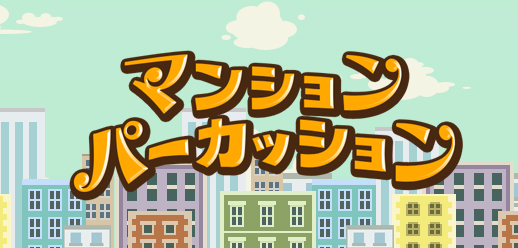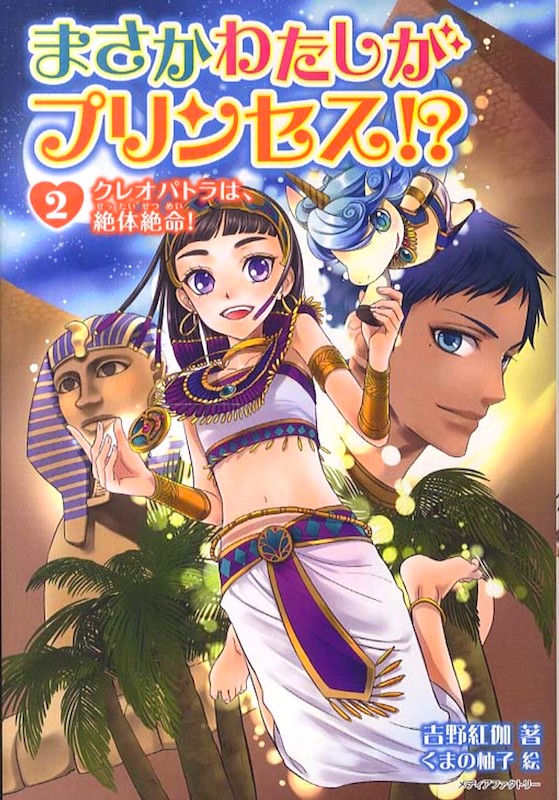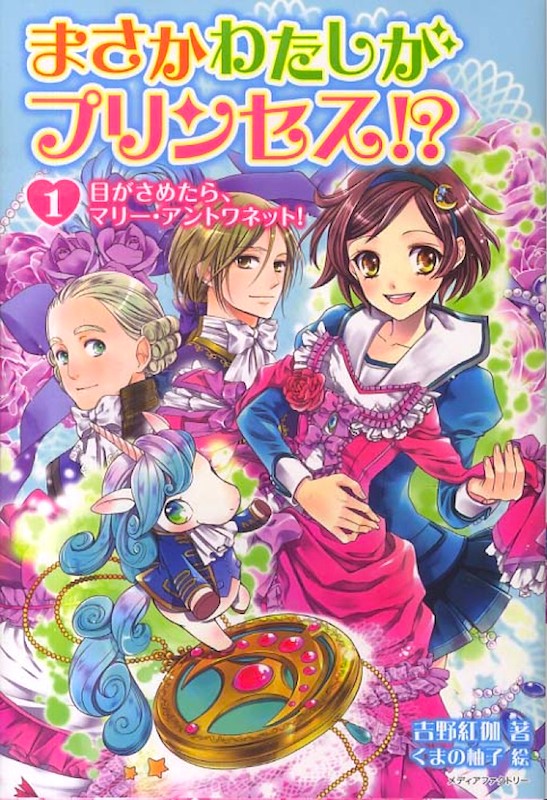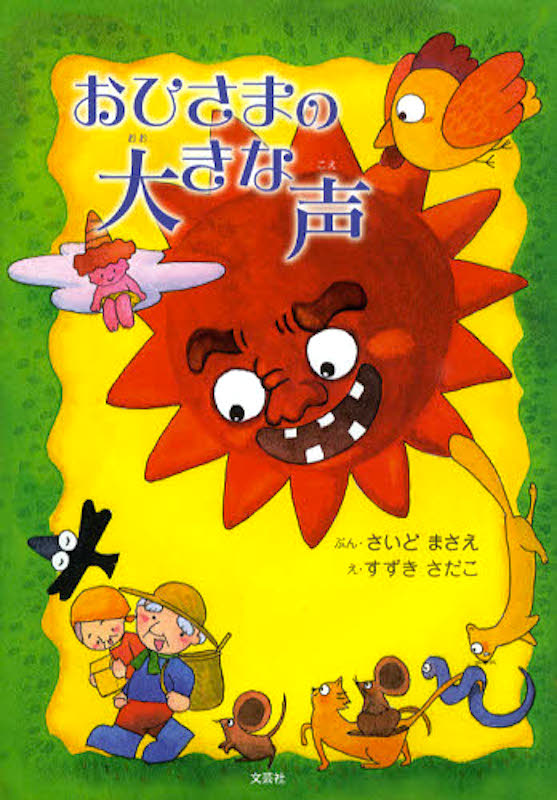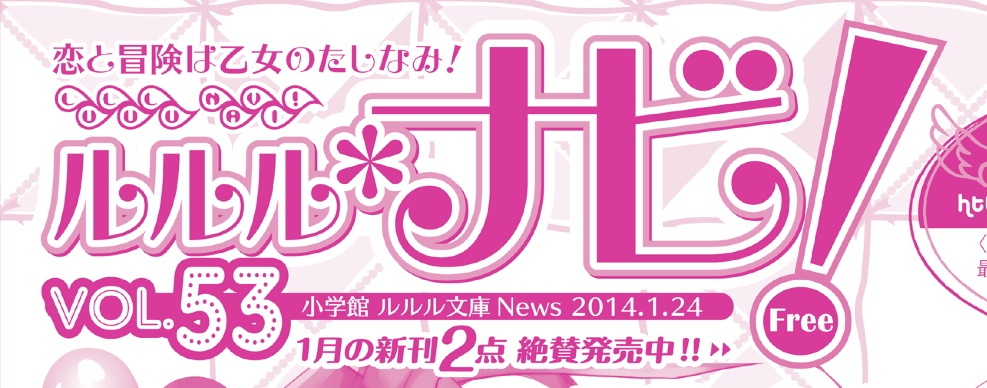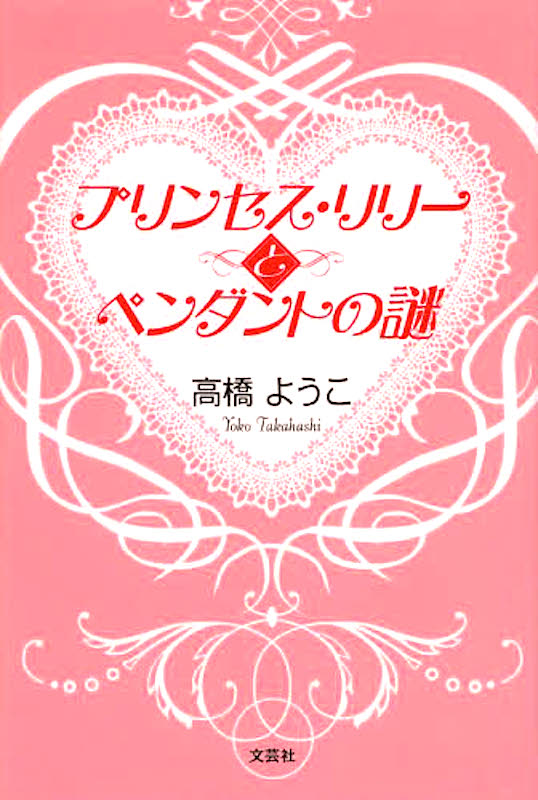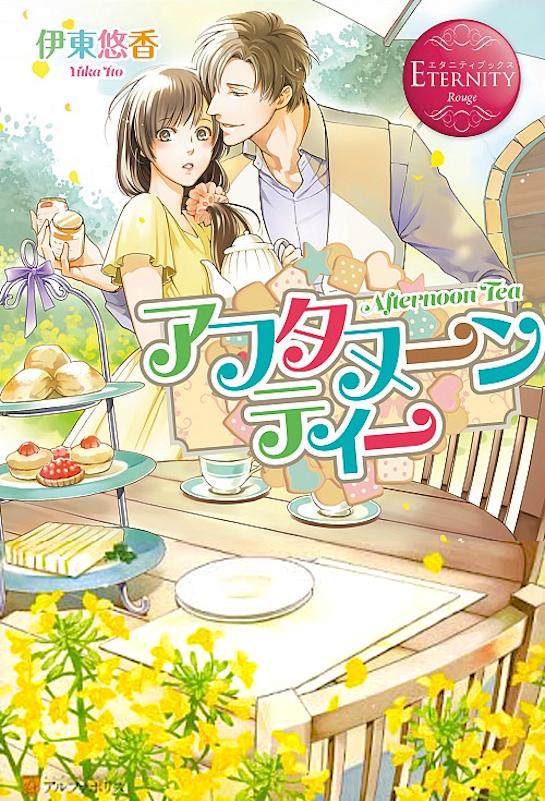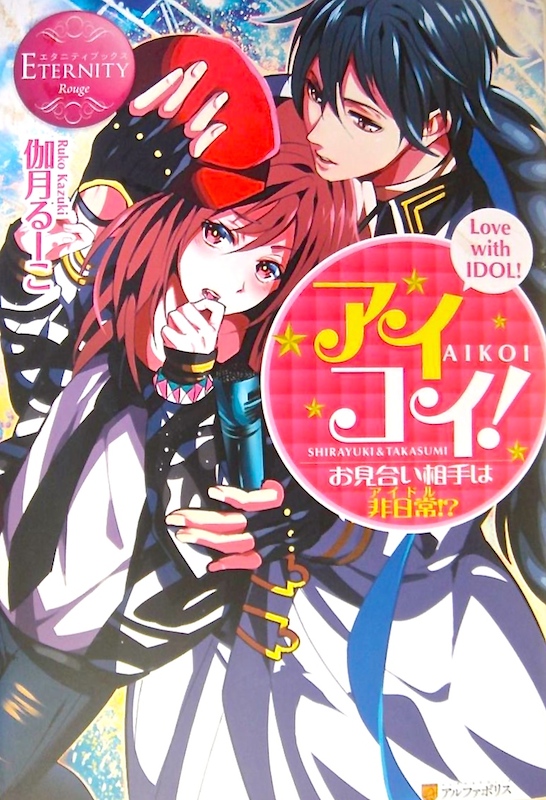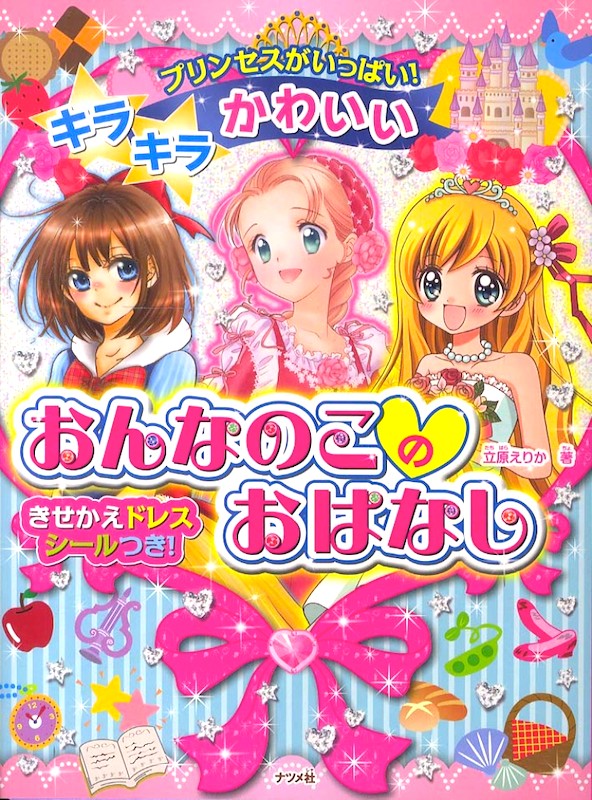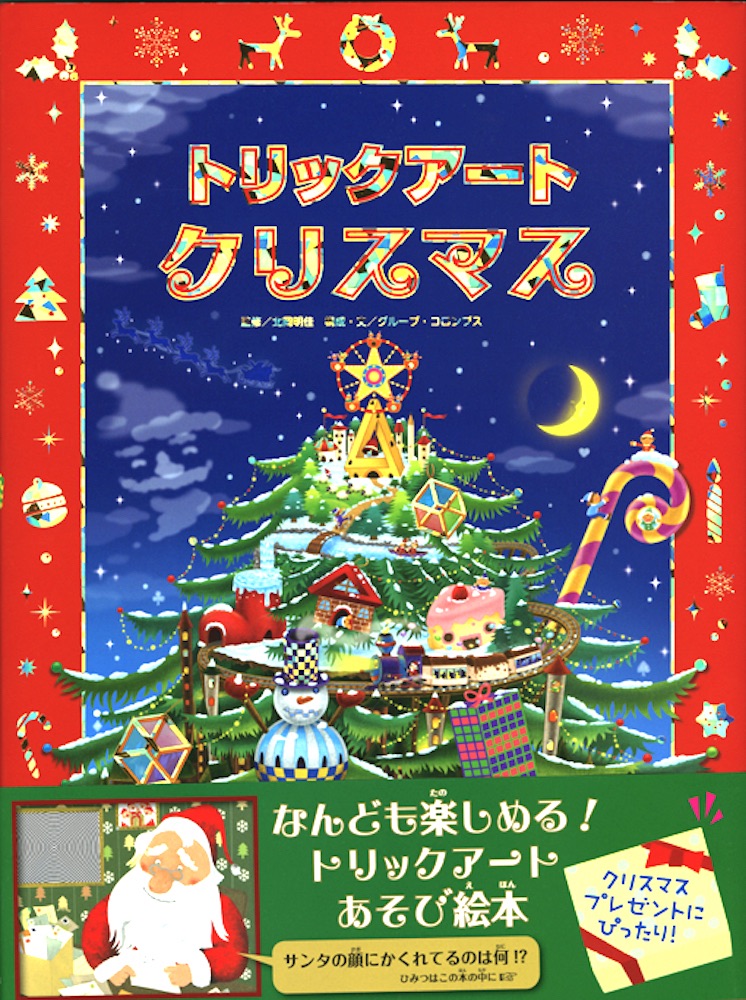
商店街の看板 さとうゆたか
荒川区三の輪の有名な商店街。
絵本 さとうゆたか
書名:名作おひめさまものがたり
著者:オチアイトモミ
発行:学研プラス
児童書 さとうゆたか
書名:うらない★うららちゃん 2
著者:もとしたいづみ/作 ぶーた/絵
発行:ポプラ社
こちらが1ですね。
店の看板 さとうゆたか
テレビを見ていたら出てきた、加賀山代温泉のお店。
ネット上にあった「べいびい」さんの写真を拝借しました。
サンエイムック さとうゆたか
書名:霊感体質かなみのけっこう不思議な日常6
著者:吉野奏美 川添真理子
発行:三栄書房
コンビニの幟旗に さとうゆたか
近所のコンビニの前に立ってました。
ラジオ番組のロゴ さとうゆたか
「ももくろくらぶ」は、ニッポン放送をキーステーションに、全国23局で放送されているラジオ番組。
バーゲンのロゴ さとうゆたか
サンポップマチヤというショッピングビルのバーゲンセール(冬期)。
促音の「ッ」の位置と大きさが不自然…。
濁点と半濁点が変えられている…。
無料お試し版の清音フォントかも。
こちらが夏季用。
震災を乗りこえ繋いだ小さな命 さとうゆたか
書名:ふくちゃんとつくば
著者:文・おかの 絵・うさ
発行:文芸社
連載漫画のタイトルロゴ さとうゆたか
誌名:月刊YOU7月号
題名:むすまん
作者:上田倫子
発行:集英社